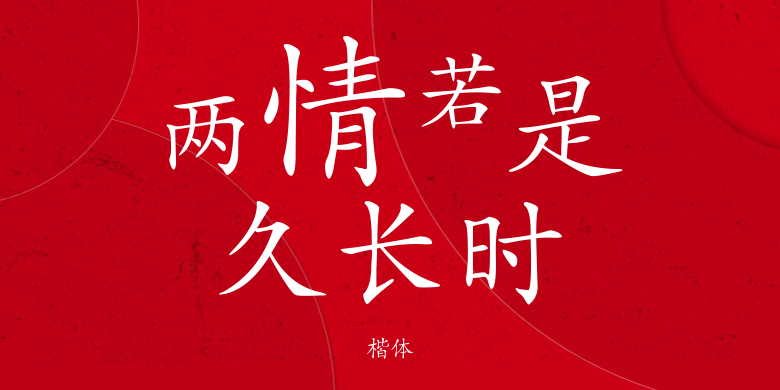
楷体
楷体,这款字体结构工整、笔画清晰,兼顾美观与易读性,适用于标题、正文、海报、包装、LOGO 等多种场景。字形优雅稳定,风格百搭耐看,适配日常排版与创意设计,让文字呈现更舒适、更具质感。楷体一笔一画,皆是细节,以均衡的比例、流畅的线条打造舒适视觉体验,字形端正大气,风格简约现代。无论是商业设计、品牌宣传还是日常排版,都能轻松驾驭,让文字更有格调与力量。楷体字体下载。